Es la porción de la letra minúscula que sobrepasa hacia abajo la línea de base. Las relaciones proporcionales entre las diferentes alturas y partes de una letra, son particulares de cada familia tipográfica.
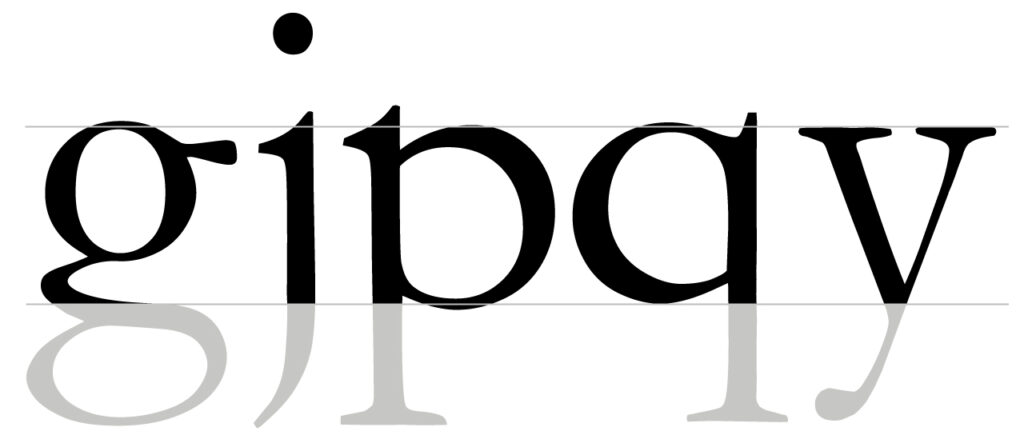
Es la porción de la letra minúscula que sobrepasa hacia abajo la línea de base. Las relaciones proporcionales entre las diferentes alturas y partes de una letra, son particulares de cada familia tipográfica.